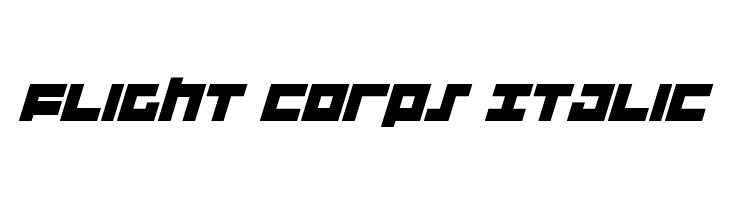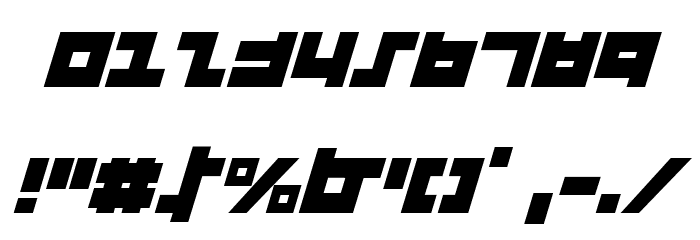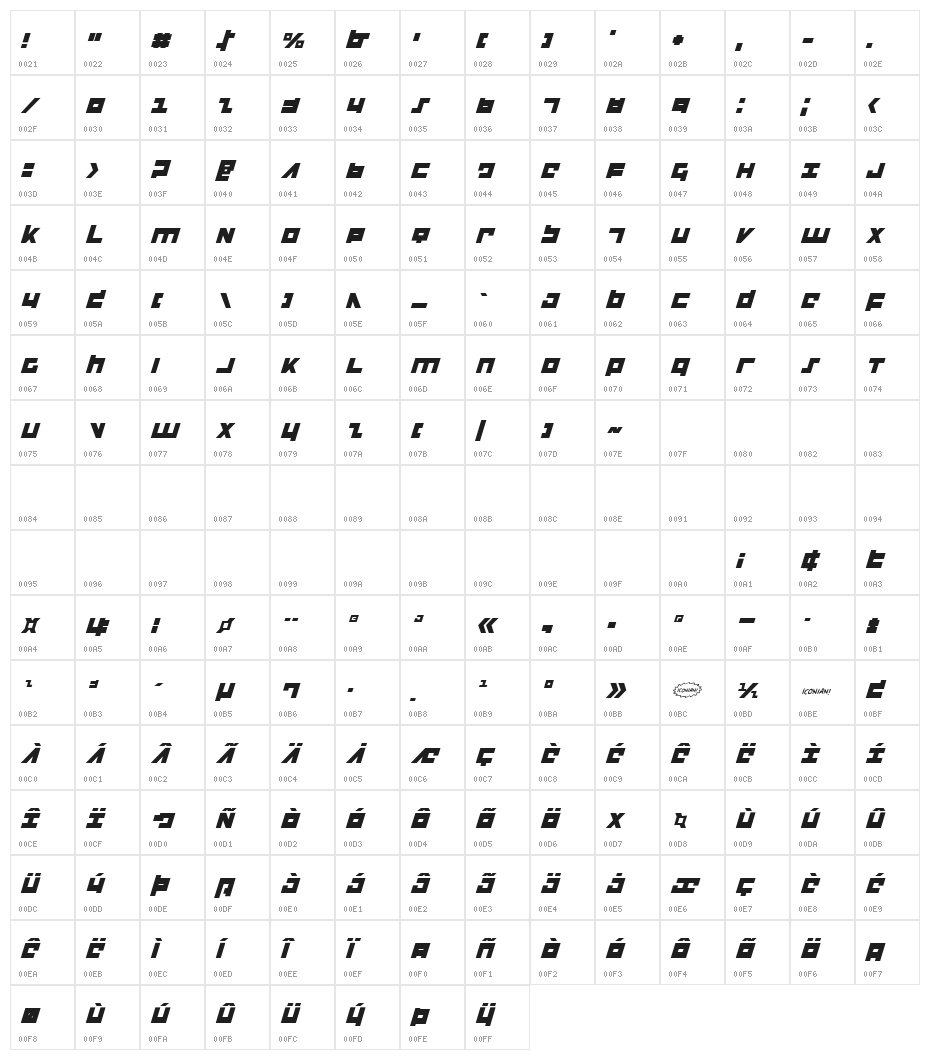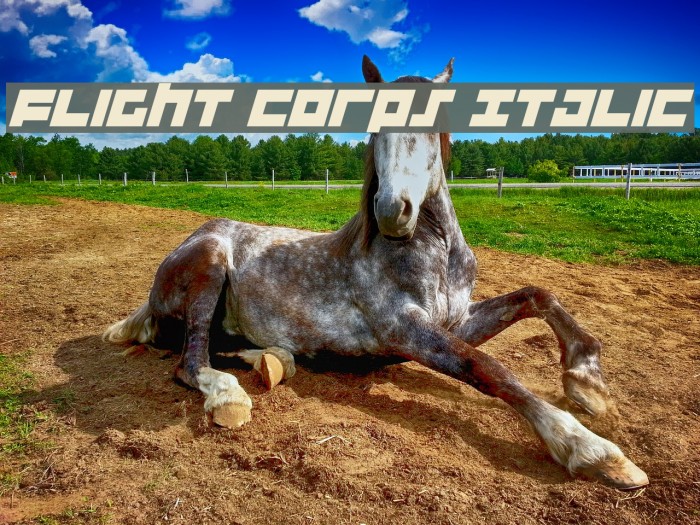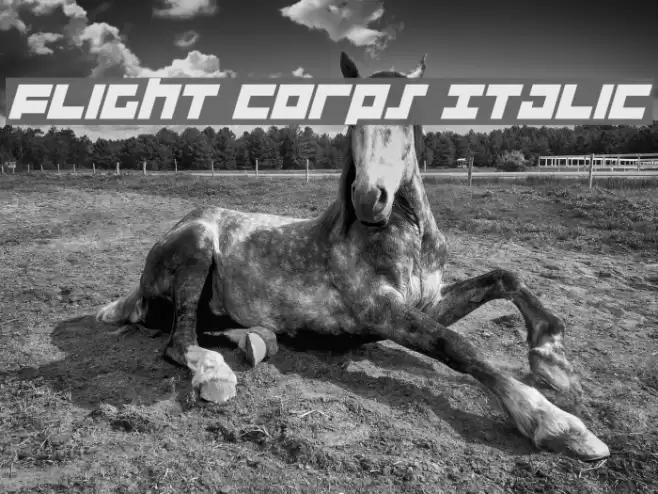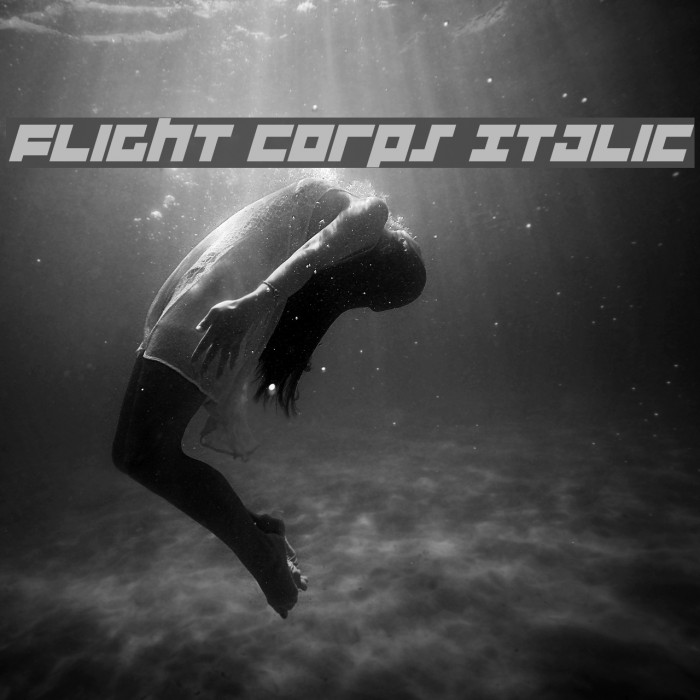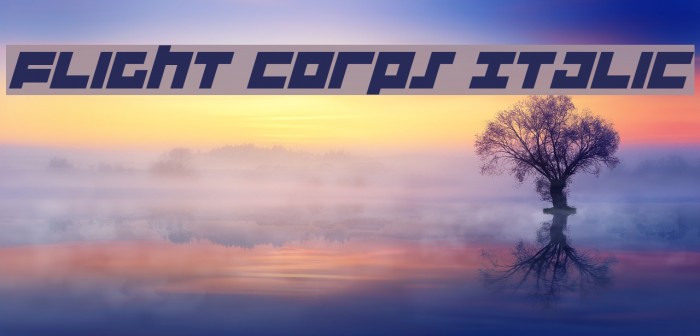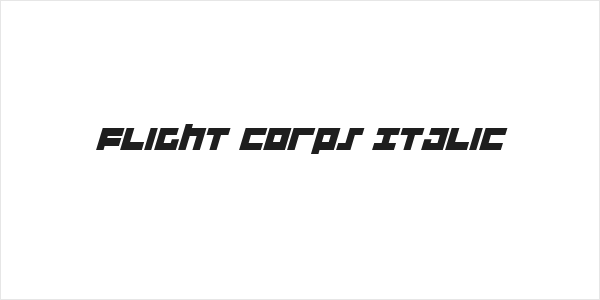
Flight Corps Italic Font
| Nombre | Flight Corps Italic |
| Peso | Italic |
| Proyectos propuestos | Ideal for sci-fi movie posters, video game titles, technology branding, and sports team logos. |
Flight Corps Italic